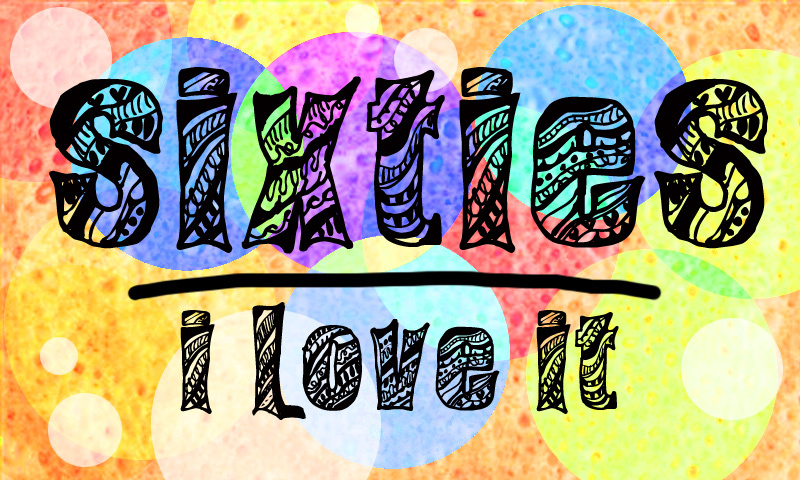
Sixties Regular von CloutierFontes ist eine kostenlose psychedelische Display-Schrift mit dem handgezeichneten Flair von Postern aus den 1960er-Jahren. Die Buchstaben wirken wellenförmig und theatralisch. Mit ihren geschwungenen Konturen und gestreiften, gemusterten Füllungen erinnert das gesamte Schriftbild eher an handgemalte Werbeschilder als an gewöhnliche Typografie.
Die Schrift eignet sich hervorragend für Albumcover, Festivalplakate, Boutique-Verpackungen, Retro-Café-Branding und Magazin-Titelzeilen, bei denen ein wenig Dynamik in den Buchstaben das Thema unterstreicht. Da es sich um eine kostenlose Schrift handelt, kommt sie besonders gut in kurzen Titeln, logoartigen Wortmarken und Titelkarten zur Geltung, da das lebendige Innenleben der Buchstaben schon bei wenigen Zeichen für einen fertigen, grafischen Look sorgt.